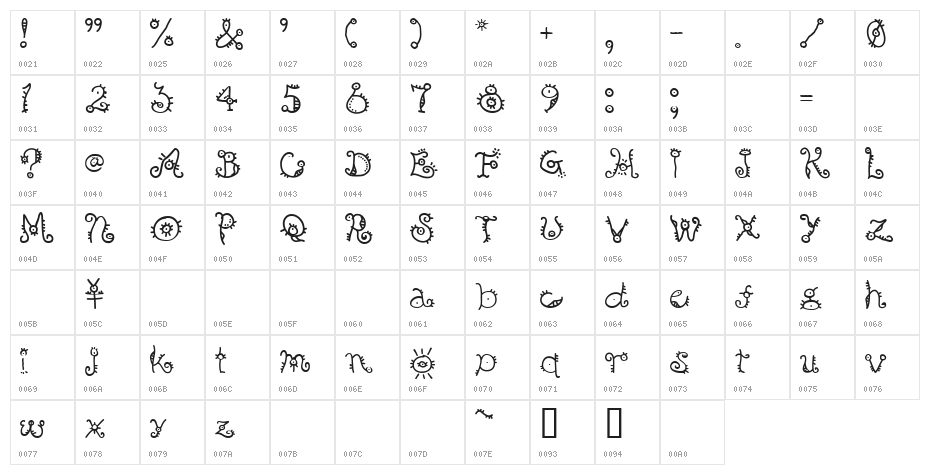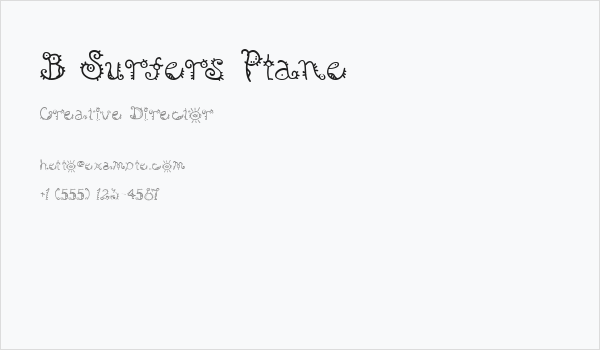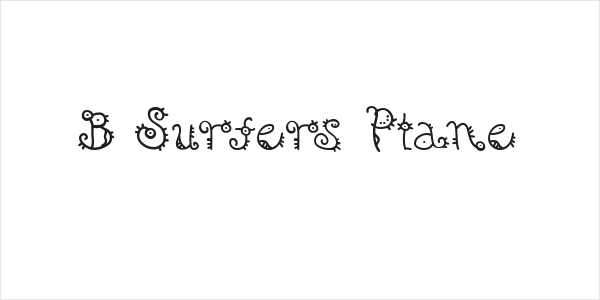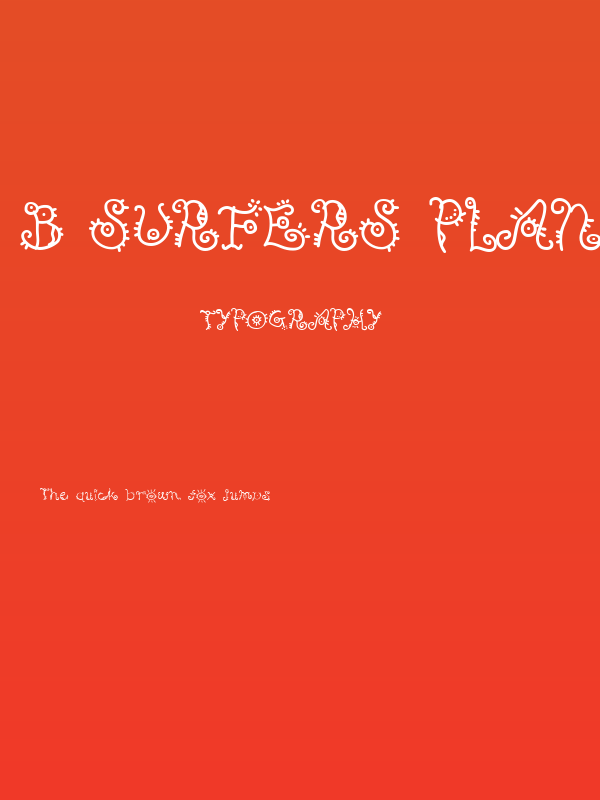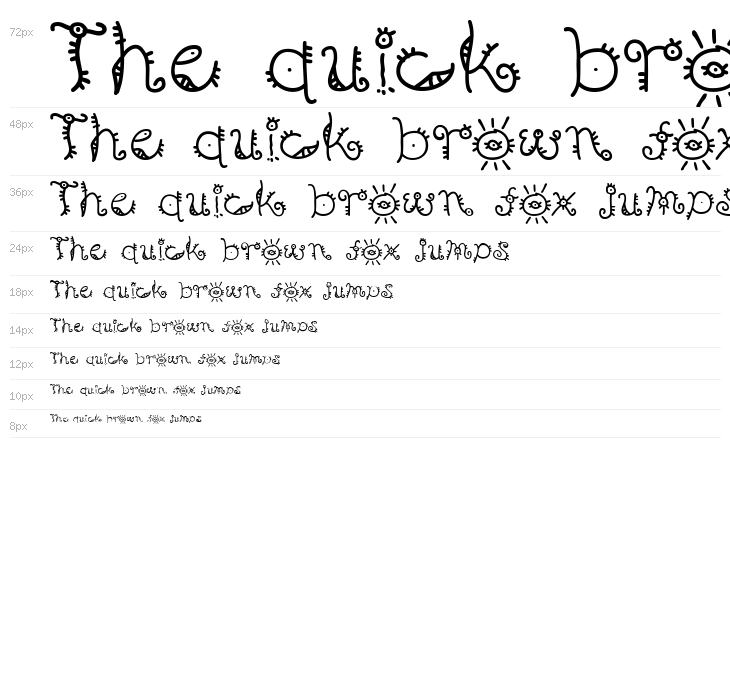
B Surfers Plane Font
| Gesamtstil | Playful, Whimsical, Creative |
| Anwendungsfall | Headlines, Logos, Artistic Designs |
| Vorgeschlagene Projekte | Children's books, playful branding, artistic designs, party invitations, and creative posters. |